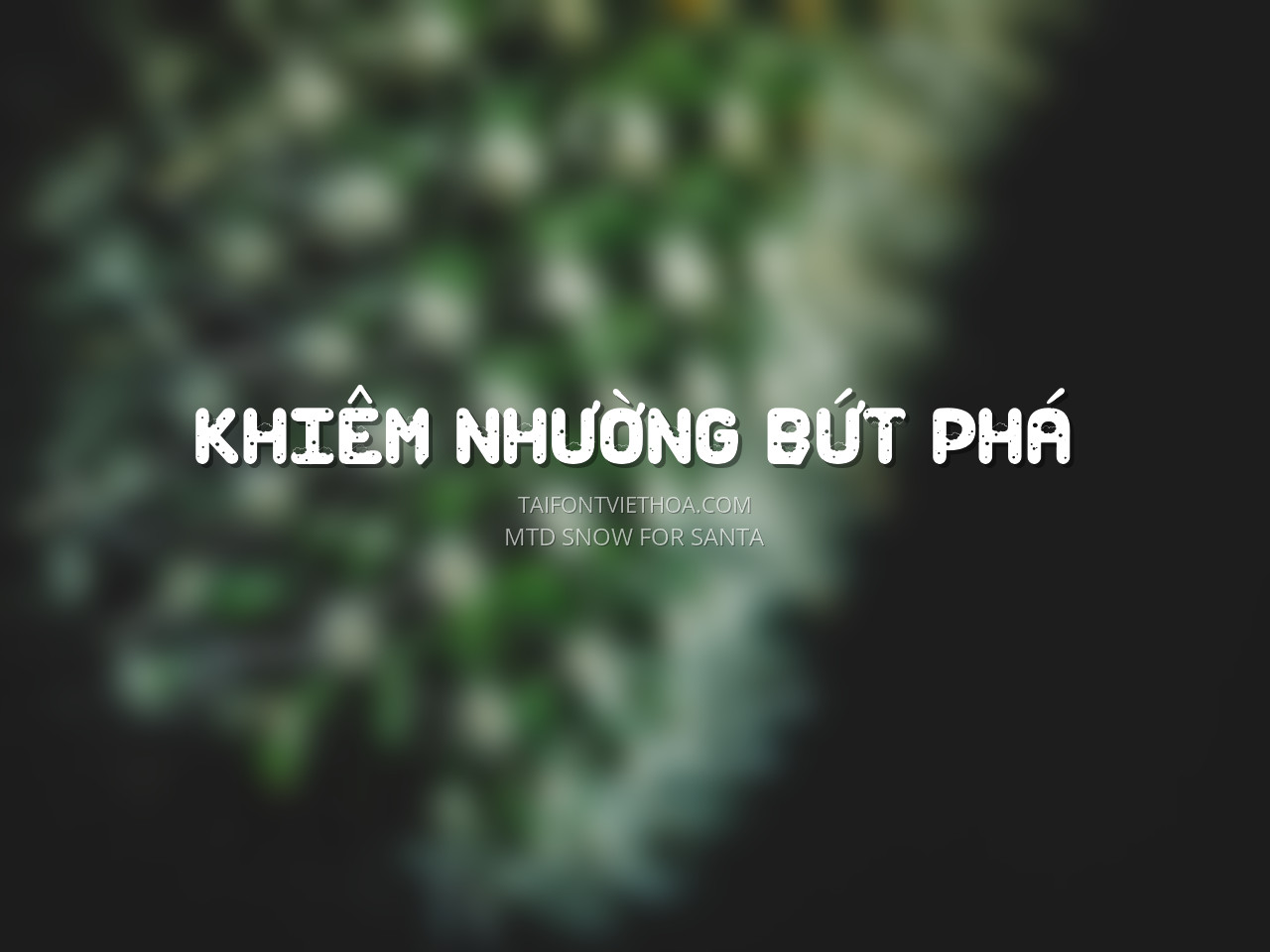
Font việt hóa MTD Snow For Santa
Giới thiệu về font Snow For Santa
Snow For Santa là một font viết tay đáng yêu, đậm không khí lễ hội Giáng sinh, được thiết kế bởi Motokiwo Type (MTD) – studio nổi tiếng với các bộ font sáng tạo mang màu sắc cảm xúc và ứng dụng cao trong thiết kế đồ họa mùa lễ hội. Font lấy cảm hứng từ những tấm thiệp, biển hiệu và hộp quà trang trí trong mùa đông, với các đường nét tròn trịa, mềm mại và pha chút tuyết phủ sinh động. Phiên bản Việt hóa do chính MTD thực hiện, hỗ trợ đầy đủ dấu tiếng Việt cùng hơn 60 ngôn ngữ khác, mang lại sự linh hoạt tuyệt vời cho mọi dự án thiết kế mùa Giáng sinh.
Đặc điểm thiết kế và ứng dụng của font Snow For Santa
Font sở hữu đường nét bo tròn, ngộ nghĩnh với phần đầu chữ mô phỏng hiệu ứng tuyết phủ, mang lại cảm giác ấm áp và vui nhộn. Ký tự được thiết kế cân đối, dễ đọc, phù hợp cho cả tiêu đề và văn bản trang trí. Các chi tiết cách điệu nhẹ tạo điểm nhấn nhưng không làm giảm tính ứng dụng thực tế.
Snow For Santa đặc biệt phù hợp với các thiết kế như: thiệp Giáng sinh, hộp quà lễ hội, banner sự kiện cuối năm, poster ưu đãi mùa đông, bao bì bánh kẹo hoặc đồ chơi trẻ em. Ngành nghề lý tưởng gồm: quà tặng, thực phẩm, giáo dục mầm non, thương hiệu mùa lễ hội và quảng cáo sản phẩm Giáng sinh.